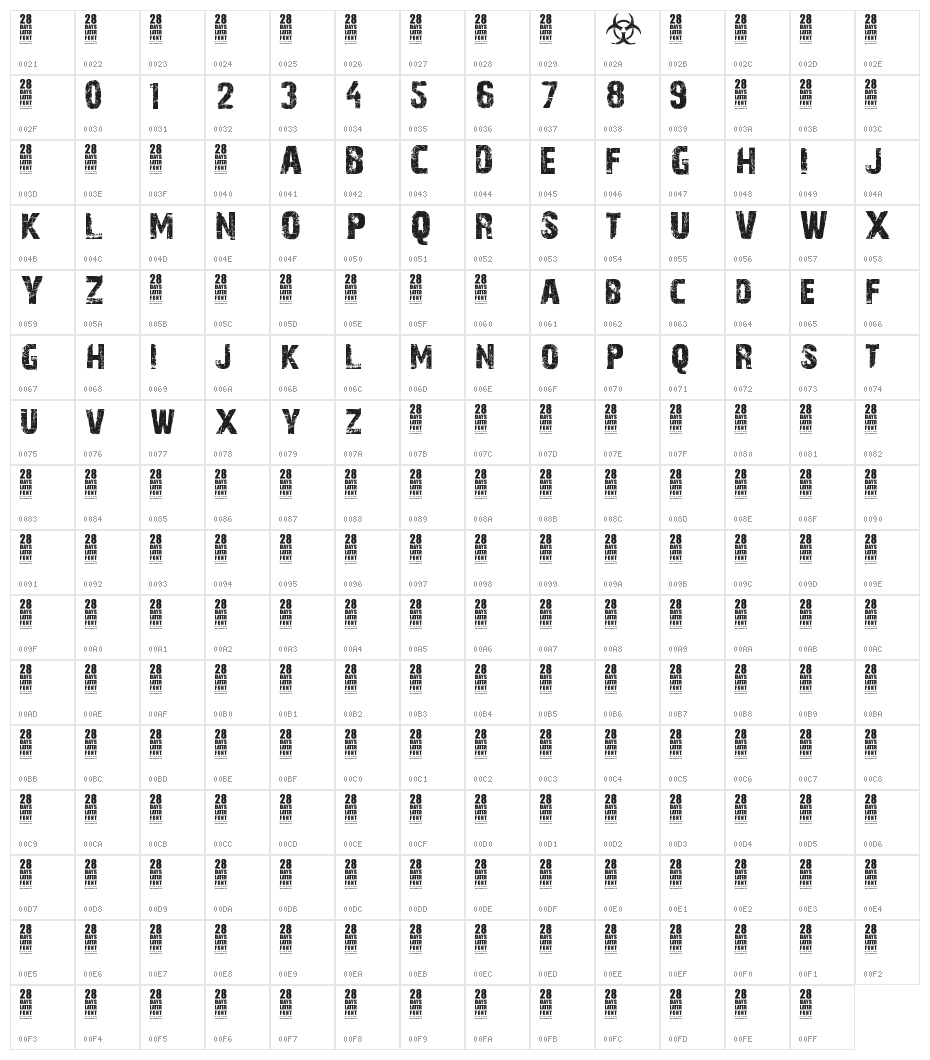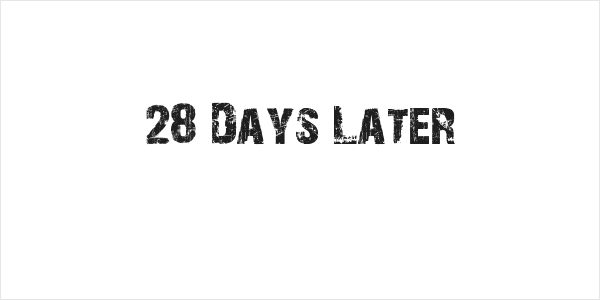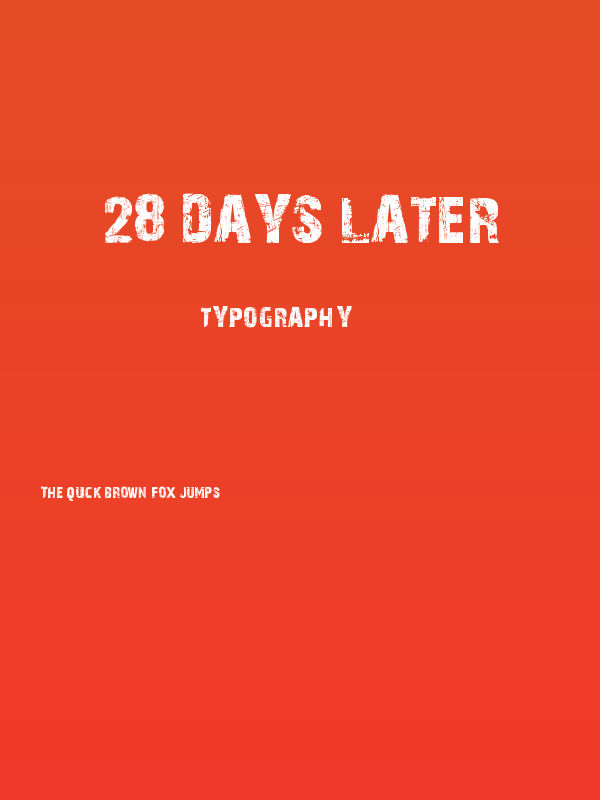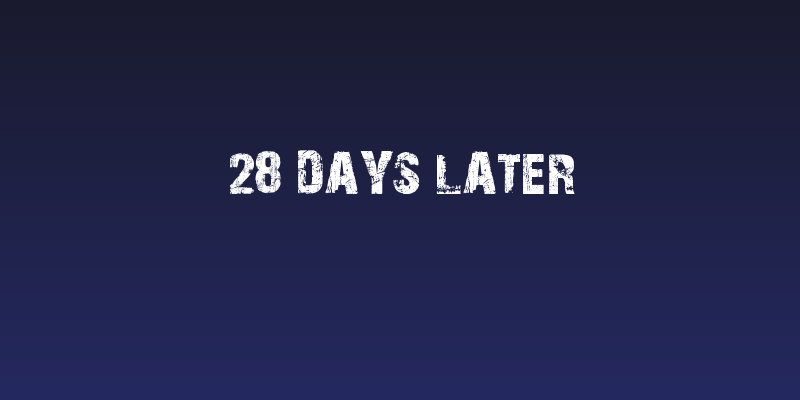
28 Days Later Font
✎ Distorted Eroded
| Gesamtstil | Grunge, Urban, Distressed |
| Vorgeschlagene Projekte | Ideal for movie posters, album covers, video game titles, and any design needing a gritty, edgy look. |